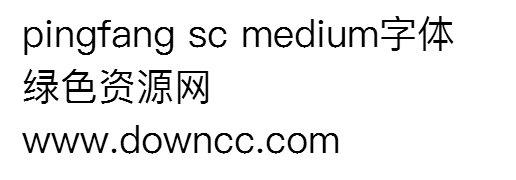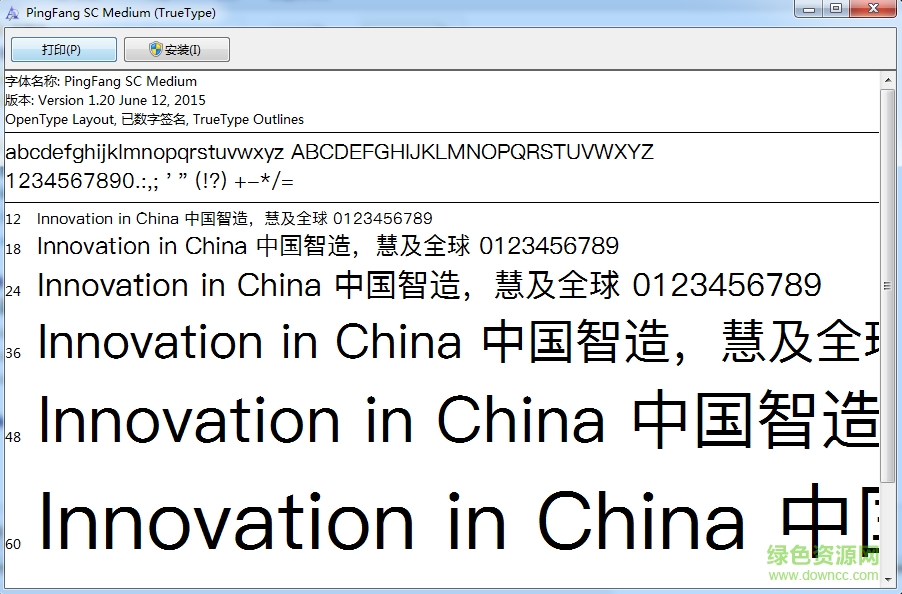
平方 sc medium字體是一款支持MAC系統(tǒng)的英文系統(tǒng)字體,字跡端正精簡,適合于平面設計、排版設計等多種行業(yè),歡迎大家在綠色資源網下載otf字體格式!
PingFang SC Medium,也叫蘋方中等體,即蘋方字體中的中等字重,是支持MAC osX系統(tǒng)的字體。